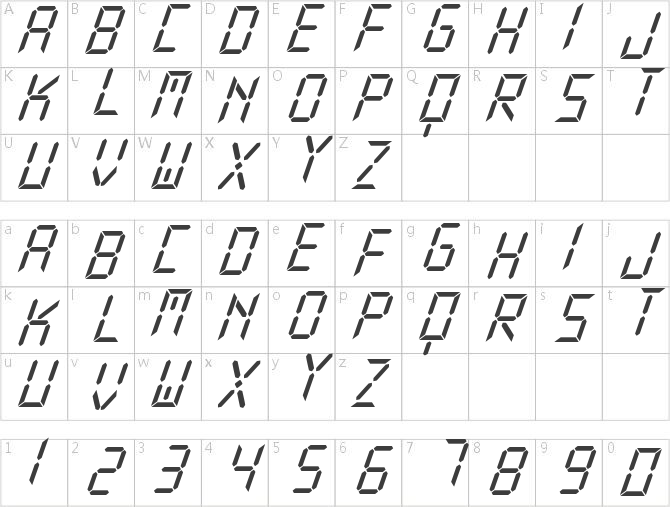
New X Digital tfb Cursive
New X Digital tfb Cursive介绍
New X Digital tfb Cursive字体字库是一款让人赏心悦目、百看不厌的英文字体,适合各类广告和产品包装设计应用,字体大小0.04MB,格式为ttf字体,上传用户是我,Dirac,作者/版权方为未知